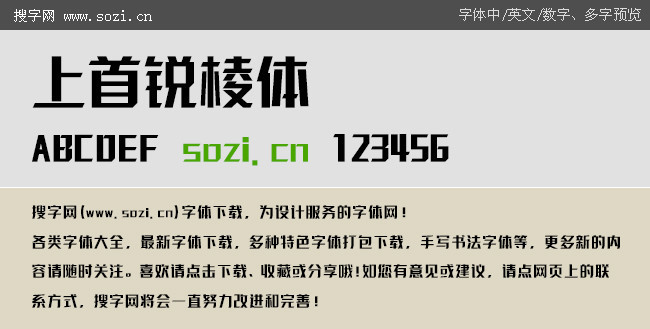
上首銳棱體
搜字網(wǎng)給大家提供一款上首銳棱體中文字體下載,上首銳棱體是一款中文簡體創(chuàng)意字體,約6763字,字體筆畫加粗,橫豎筆進(jìn)行了改良,整體直線處理,字體有剛正不阿,形態(tài)端莊特點。適用于網(wǎng)頁設(shè)計、海報設(shè)計、書籍裝幀、包裝設(shè)計等應(yīng)用。